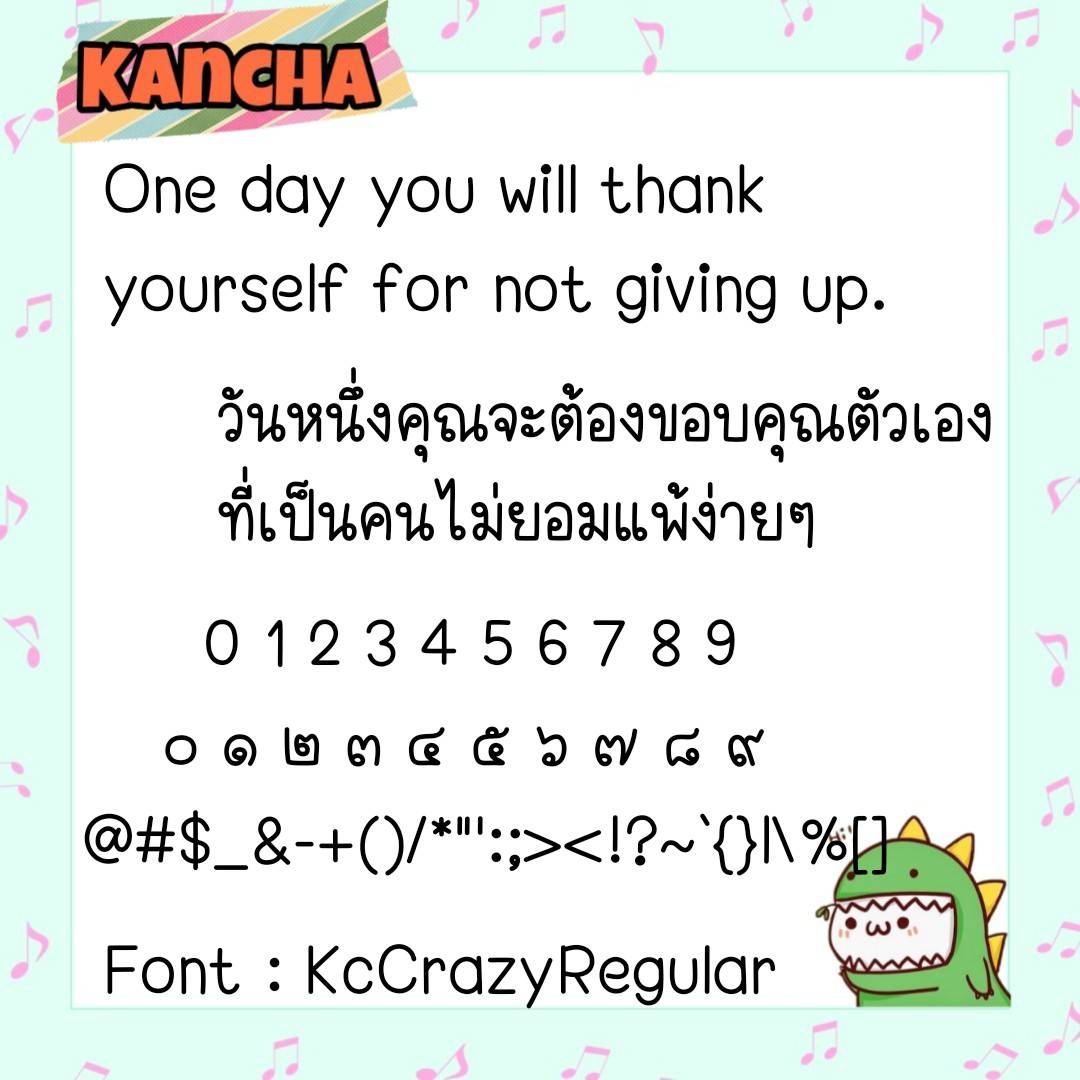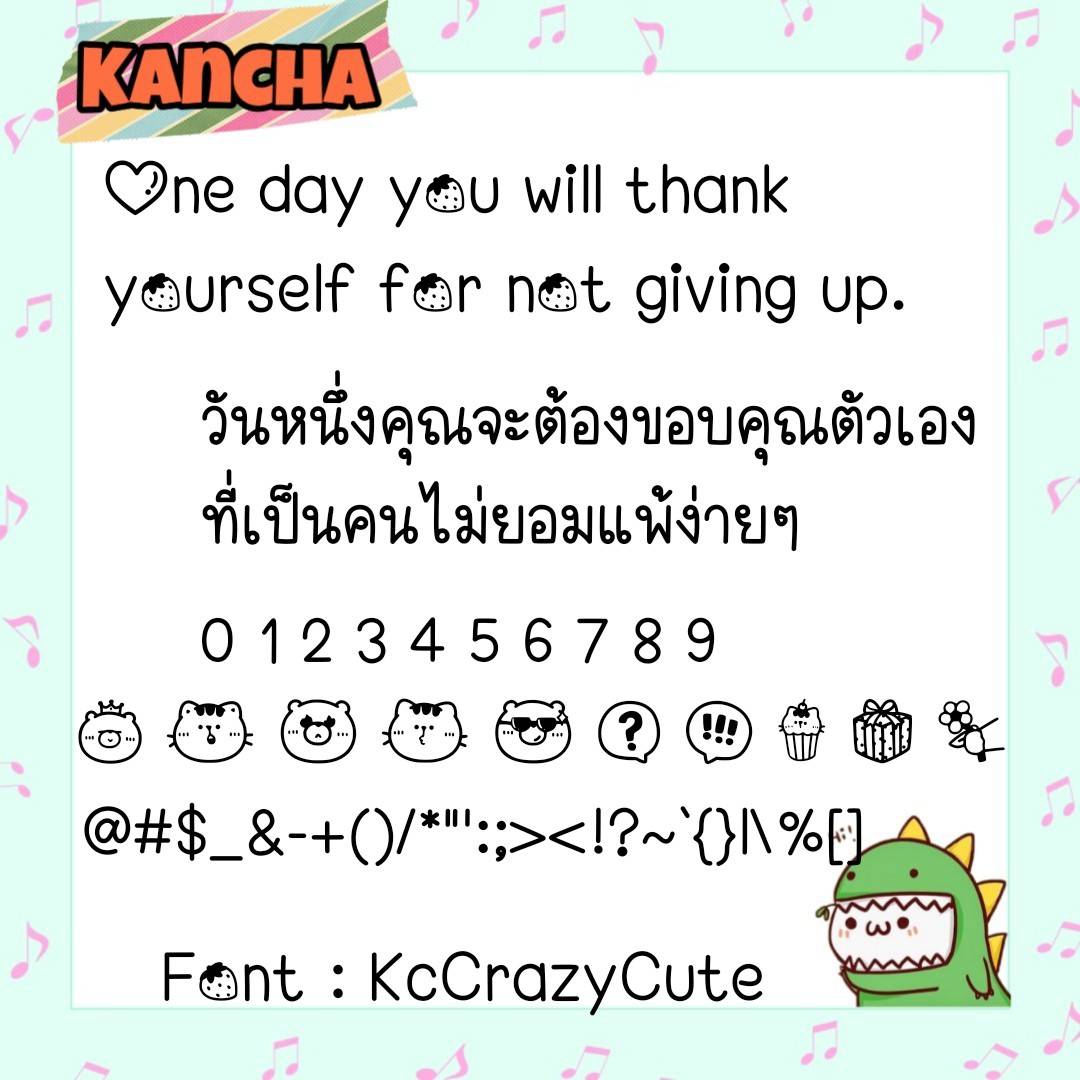
Font KcCrazy
ชื่อสินค้า : Font KcCrazy 💙
🔸ฟอนต์นี้เป็นฟอนต์อ่านง่าย ดูน่ารัก มีอิโมจิน่ารักๆแทนเลขไทยให้ด้วยค่ะ 🥰🥰
🔹This font is easy to read, looks cute, has cute emojis instead of Thai numbers.